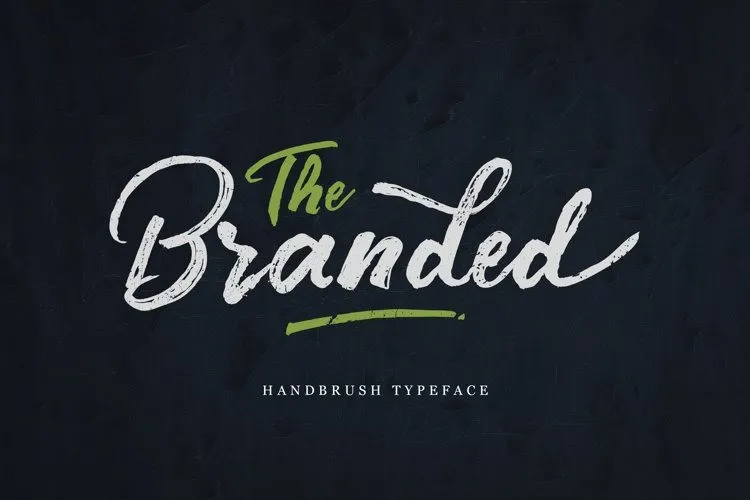
Branded Font – Download Grátis
Esta fonte tipo foi criada pela Unicode e é uma fonte com traço de pincel que traz duas estilos limpos e irregulares, mais ainda uma adição extra de traços de pincel para um impressiono natural. Este conjunto de caracteres oferece alternativas e novas sensações visuais ao designer ou artesão em trabalhar com projetos variados. Não é à toa que a fonte se tornou tão popular entre os criadores; ela transmite uma atmosfera vintage e moderna, perfeitamente adequada para criar texturas interessantes e design de logotipos. Escolha esta fonte se estiver buscando algo que traga um elemento único e vivo ao seu trabalho gráfico.